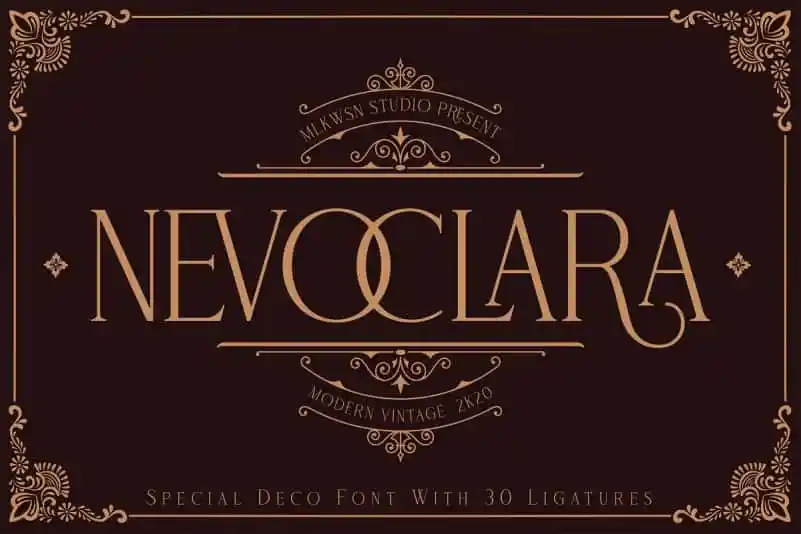
Nevoclara Modern Vintage Font – Download Grátis
Esta fonte é inspirada nos cartazes vintage de viagem e nas revistas antigos. Seu design exibe a elegância e o charme dos anos 1920, quando este estilo floresceu, criando uma influência significativa na arquitetura e arte da Europa Ocidental e América do Norte durante os anos 30. A Nevoclara Modern Vintage é um tipo de display que inclui uma ampla gama de caracteres, incluindo letras maiúsculas e minúsculas em caixa alta, números, pontuação, ligações e suporte multilingue. As suas linhas delicadas e formas geométricas retratam perfeitamente a estética vintage dos anos 1930, com uma gama de alternativas de caracteres únicas que adicionam um toque pessoal ao seu uso. Especialmente para designers gráficos apaixonados por arte vintage ou arquitetura do século XX, Nevoclara Modern Vintage é o tipo perfeito para criar designs que exibem elegância e sofisticação. Seu design moderno com suporte para múltiplos idiomas permite ao designer adaptar a fonte de maneira eficiente, proporcionando um texto fluido em qualquer idioma. Escolha Nevoclara Modern Vintage para decorar seus trabalhos gráficos com o charme dos anos 1930.